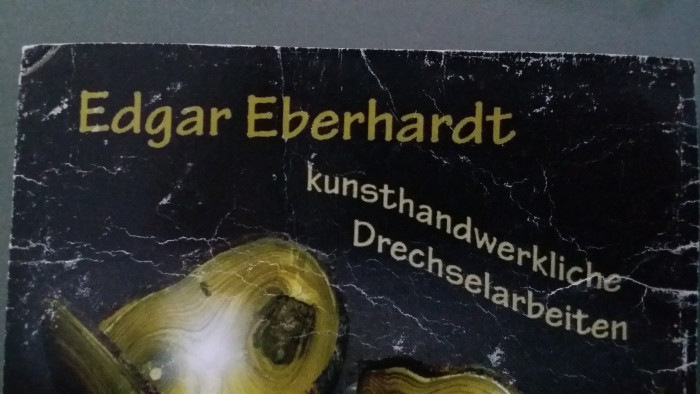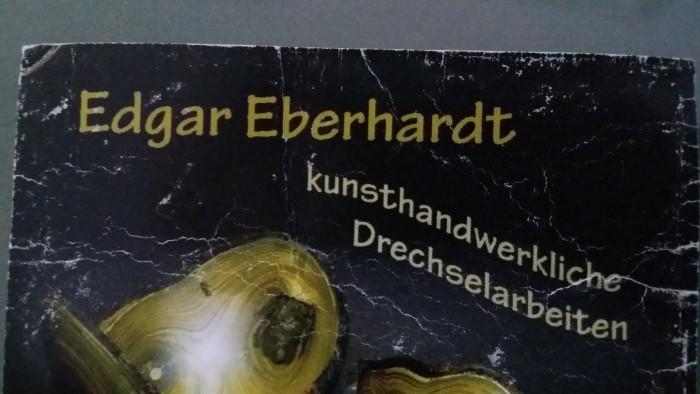
Suche diese Schriftart (Drechselarbeiten)
Servus suche diese Schriftart von der Visitenkarte habe ähnliche gefunden aber dort ist das kleine a meistens anders, vom E her könnte es in den meisten fällen passen...